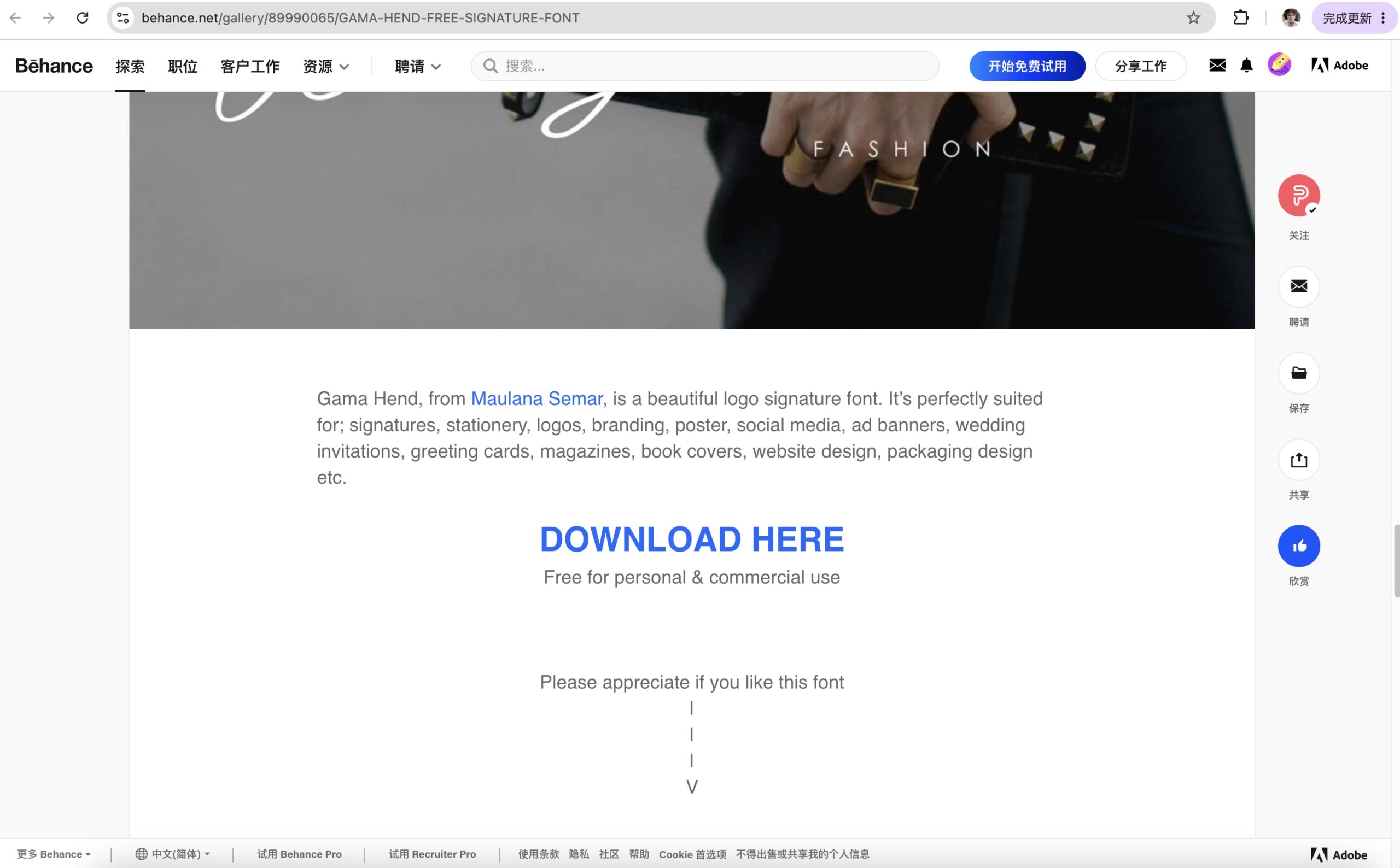
Gama Hend
Gama Hend 是一款由设计师 Maulana Semar 创作的现代手写签名字体(Signature Font)。字体以真实手写签名为设计灵感,通过流畅自然的连笔结构、纤细优雅的线条以及自由舒展的字母走势,营造出一种兼具高级感与个人艺术气质的视觉效果。
从整体字形来看,Gama Hend 采用极细笔画设计,模拟真实钢笔书写时留下的轻盈轨迹。字母之间通过自然连接形成连续流动的书写节奏,部分字母拥有夸张延伸的起笔与收尾线条,使文字呈现出类似艺术签名般的独特辨识度。相比普通装饰型手写字体,Gama Hend 更强调“个人笔迹”的表现力,让文字看起来如同设计师亲手签署一般自然。
实际应用方面,Gama Hend 凭借其自然流畅的签名感与精致优雅的视觉气质,非常适合用于强调个性与情感表达的设计场景。字体细腻的连笔结构能够为品牌 Logo 注入独特的手写识别度,尤其适用于时尚、美妆、婚礼、摄影、生活方式等注重审美体验的品牌视觉设计。
同时,其轻盈舒展的线条也适合应用于邀请函、贺卡、杂志封面、社交媒体宣传图、广告海报以及产品包装等项目,为作品增添浪漫、精致且具有私人签名般的高级氛围。在数字媒体设计中,Gama Hend 同样能够作为标题装饰字体使用,与简洁现代的无衬线字体搭配,形成富有层次感的视觉效果。
字体最大的特点在于其优雅而自由的线条表现。纤细的笔画搭配宽阔的字母比例,使整体视觉具有轻盈、浪漫和时尚的气息。长距离延展的横线、柔和的弧形连接以及不规则但富有节奏的笔触变化,共同构成了字体独特的艺术感,非常适合用于需要传递精致、私人化与高级感的设计项目。
与传统英文手写字体相比,Gama Hend 并不过度强调复杂花体结构,而是通过简洁流畅的线条保持良好的识别度。在保证优雅气质的同时,也降低了阅读难度,使其能够适应更多商业设计场景。
总体而言,Gama Hend 是一款充满女性化气质与现代时尚感的签名字体。它将真实手写的温度与数字字体的稳定性结合,为设计作品带来独特的个人印记,非常适合作为品牌 Logo、婚礼设计以及高端视觉项目中的装饰字体使用。